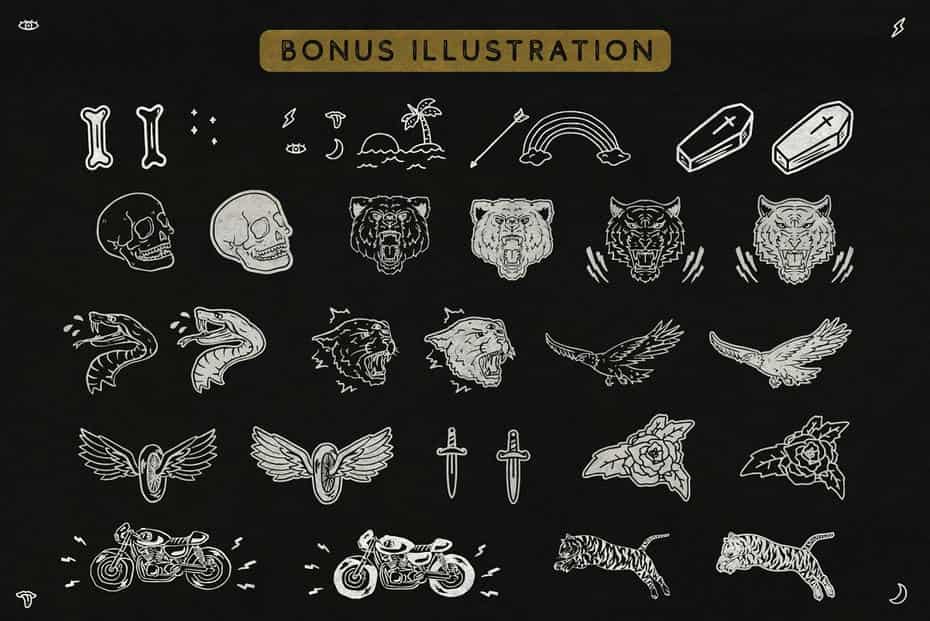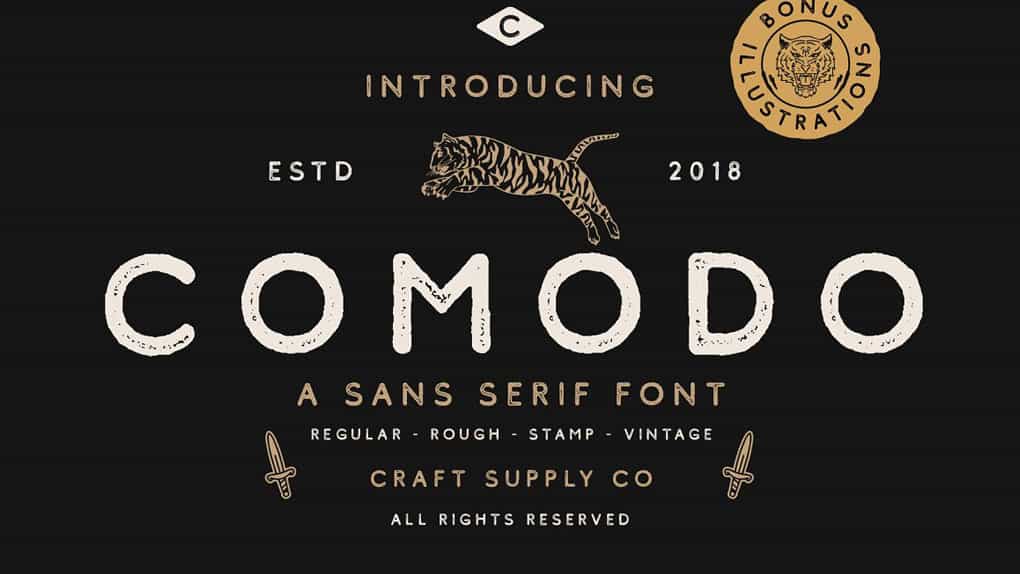
فونت انگلیسی Comodo : این فونت جذاب و منحصر به فرد دارای 4 استایل متنوع است و در بسیاری از پروژه های قابل چاپ مناسب می باشد. برای مثال اگر شما می خواهید یک کارت تبریک یا یک طرح بسته ، یا حتی یک برند تجاری ، طراحی صنایع دستی ، هر پروژه DIY ، عنوان کتاب ، فونت عروسی یا هر هدفی برای زیبا جلوه دادن پروژه هنری یا طراحی خود با خیال راحت با همه الگو ها و اشکال بازی کنید و یک طرح به روز و مرسوم ایجاد نمایید.